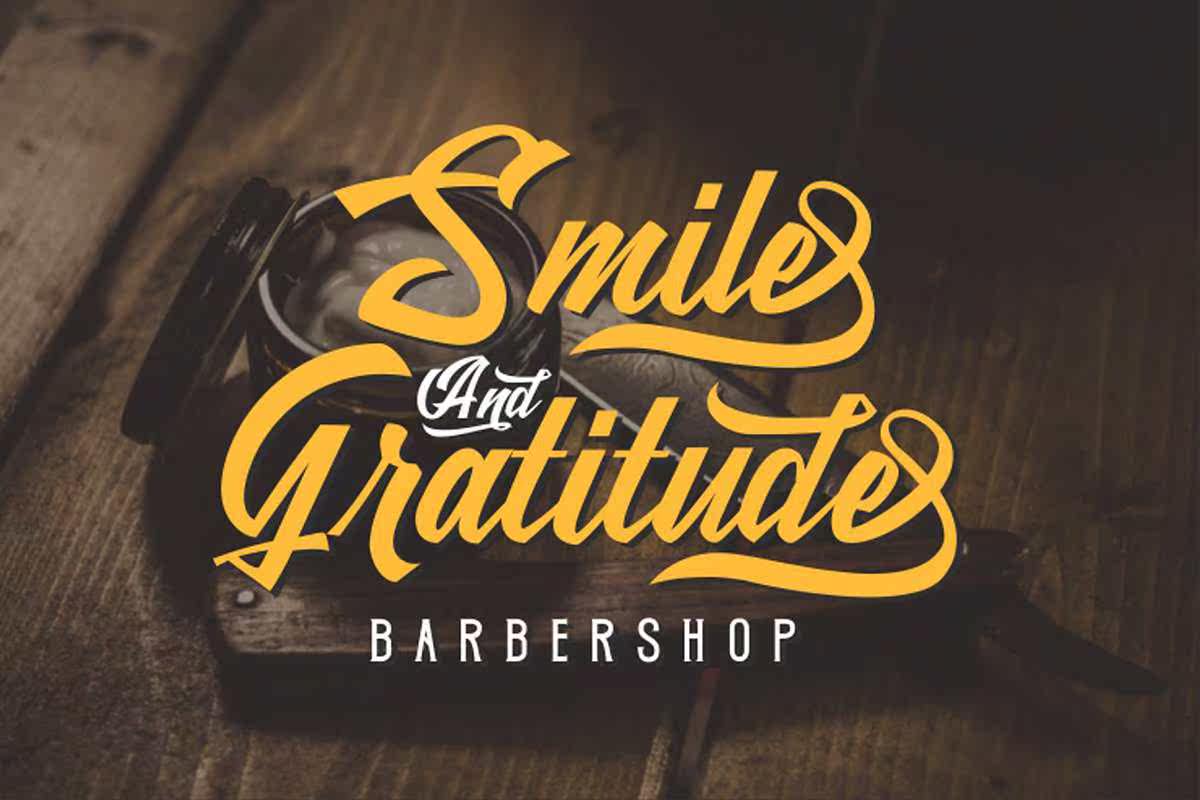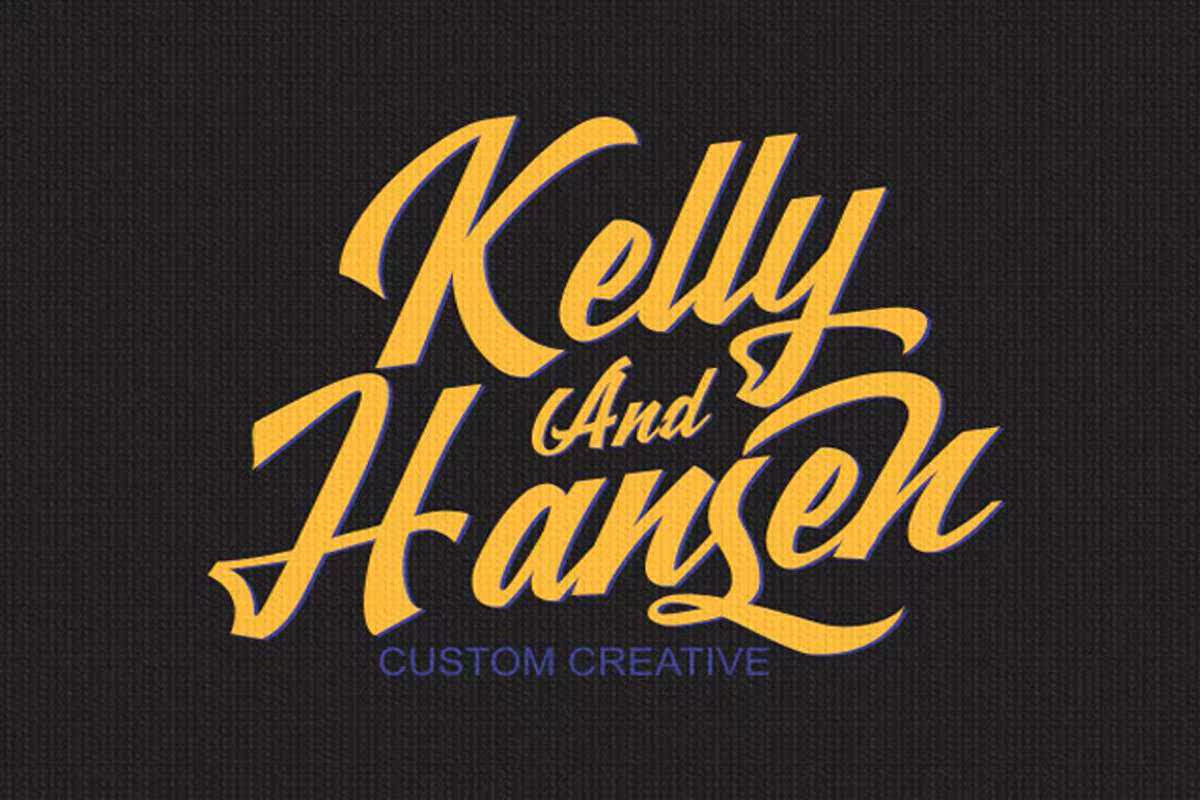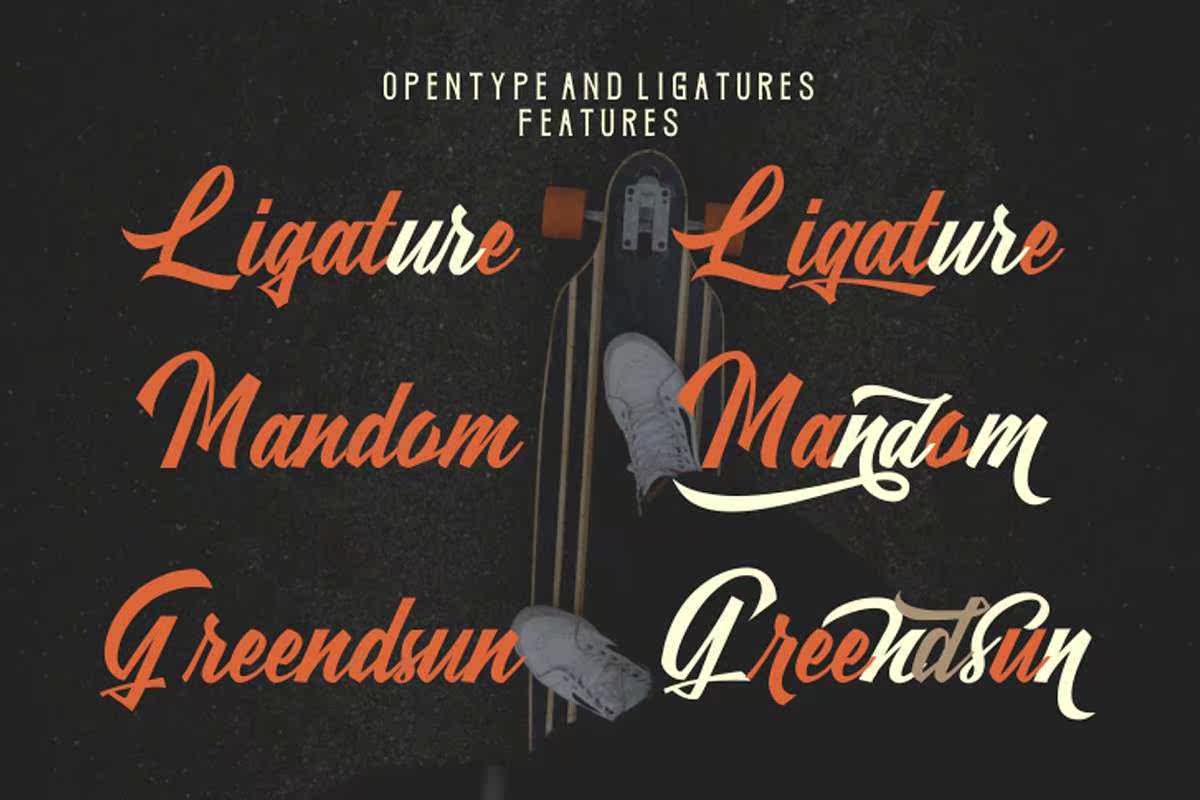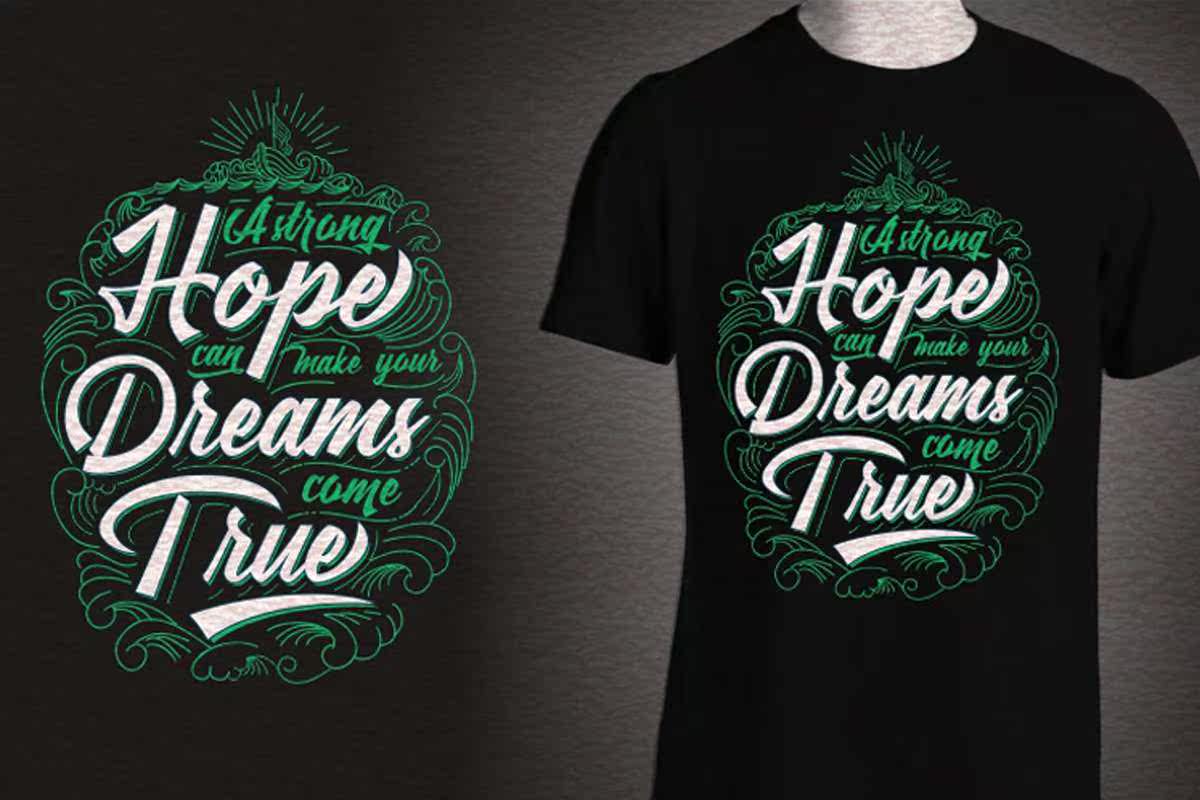
RushlandScriptisafontcreatedtobringstrong,SharpandFlexibleYoungCharacters带有平滑和可变Swashes,此Fonts是为Beinguseads的角色创建的。RushlandScriptisafontcreatedtobringstrong,SharpandFlexibleYoungCharacters带有平滑和可变Swashes,此Fonts是为Beinguseads的角色创建的。